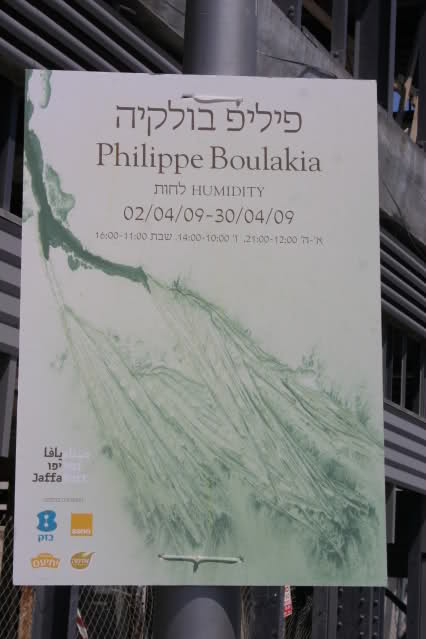
„Hebräische Kursivschrift“
D P Sch / M O D
DAS ist ja krass.
Mich hat das auch immer fasziniert beim japanischen, wie sie Fremdwörter "einsilben" in ihr Schriftsystem. Wenn man aber genauer drüber nachdenkt: wir machen das ja genauso, wenn wir z.B. russische Namen mit lateinischen Buchstaben schreiben wollen (?????????? --> Schostakowitsch / Šostakovi?), oder natürlich auch japanische (?? --> Tenn?). Die fremden Zeichen könnte man bei uns noch viel weniger lesen und aussprechen, also eine mehr oder weniger umständliche Transliteration.
Warum also nicht auch bei Bands :)
(J-Rock-Bands machens ja eher umgekehrt: englische Namen, die dann wieder mit japanischen Zeichen geschrieben werden)
Die Japaner haben echt eine superspannende Jongliererei mit Sprachen und Alphabeten drauf, manchmal komplett durcheinander und über Kreuz.
Endgültig offtopic (sorry), mein Lieblingsbeispiel (gefunden in Shinjuku vor vier Jahren):
Da steht:
Sakuraya [Warenhauskette, lit. «Kirschblütenhandlung»; also jp. ausgeschrieben in Hiragana]
Wottchi [«Watch»; also englisch transliteriert in Katakana]
kan [?, sowas wie Haus, Halle etc.; also jp. transliteriert in Romaji]
Nein, das gehört zum Depeche Mode CI :-)
Frage: Ist das "#"-artige Zeichen, das in "DEPECHE" das "D" ersetzt hat, ein hebräisches?
nein. das D ist von corbijn. genau wie das schrottige M.
Das »Nein« ist nur halbrichtig. Der Gestalter des hebräischen Plakates hat das »schrottige M« genommen, umgedreht, als hebräisches ? (Schin) verwurstet und in »Depe?« untergebracht (was natürlich sehr bemüht aussieht). Die Transliteration von »Depeche Mode« ist hier also Daleth-Pe-Schin Mem-Waw-Daleth — ist halt eine Konsonantenschrift.
Noch ein Beispiel für die Übersetzung in hebräische Schrifzeichen: